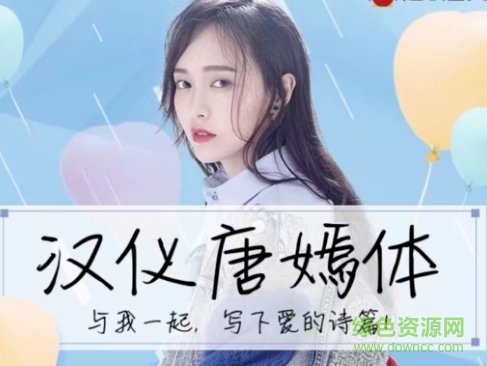
漢儀唐嫣體是在手機(jī)qq上線的一款明星手寫體,根據(jù)人氣明星唐嫣的字體打造,給人字如其人的娟秀體驗(yàn),喜歡的朋友就來綠色資源網(wǎng)體驗(yàn)吧!
與我一起,寫下愛得詩篇,記錄美好瞬間~
唐嫣的字進(jìn)入漢儀字庫“漢儀唐嫣體”,字如其人說字如其人,意思是說人長的好看,字也會(huì)很好看。
漢儀唐嫣體是繼徐靜蕾、井柏然后再次入圍的漢儀字體,字如其人瀟灑明亮,給你沉穩(wěn)大氣的藝術(shù)體驗(yàn),可以廣泛運(yùn)用在包裝設(shè)計(jì)、廣告策劃、排版印刷等場合。